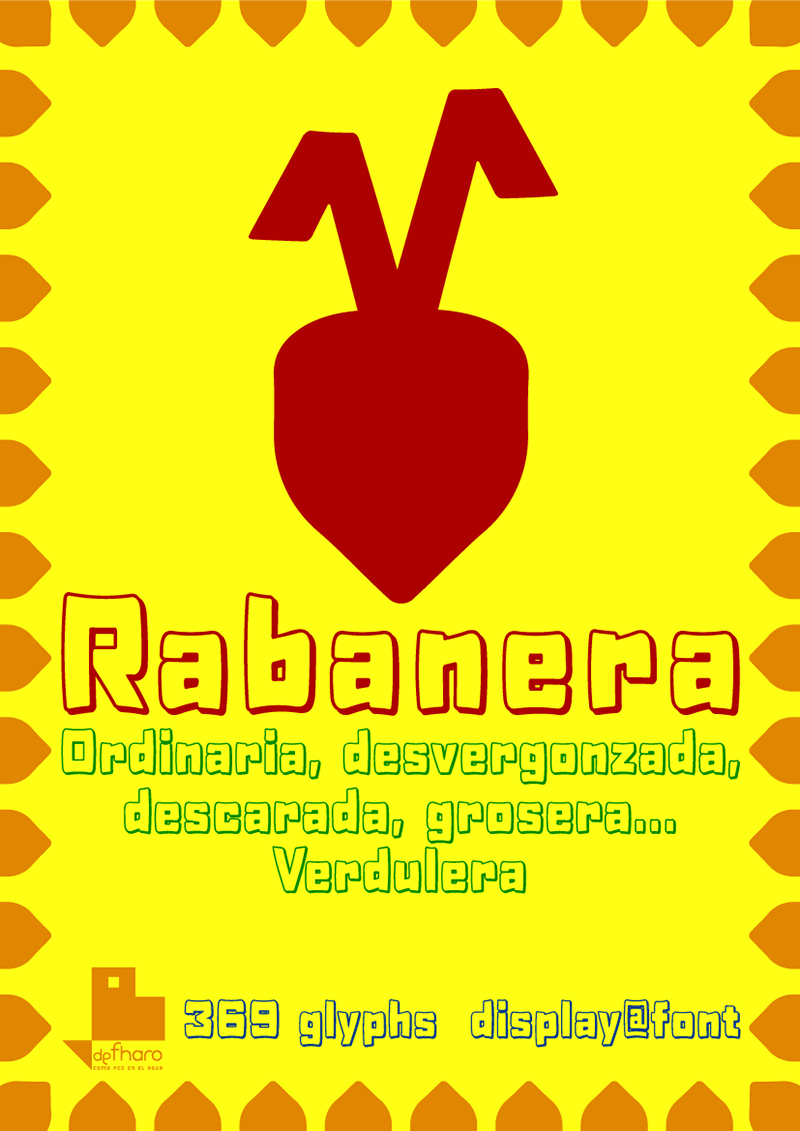
Rabanera es una nueva fuente tipográfica, basada en mi anterior diseño Hobby of night, de estilo outline + shadow, de caracter divertido esta fuente la puedes usar en diseño gráfico o editorial, por su morfología se la puede denominar: Display font.
Ideal para cualquier diseñador gráfico, esta fuente le servirá para encabezados o grandes titulares y rótulos, de perfecta legibilidad y lectura en frases largas.La tipografía está compuesta de 369 glifos, son los necesarios para usar la fuente con todos los idiomas europeos basados en el Latín, incluye el símbolo del euro y el icono del rábano construido con la letra D mayúscula, el símbolo duplicado de Radical y el símbolo less para la punta.
El nombre que he elegido para esta fuente es un ejercicio de Naming-marketing divertido que completa el proyecto, la acompaño con una lista de sinónimos, elegidos para crear espectación, a partir de la primera definición de la RAE.Según esta definición de la RAE [Rabanera]: 1. adj. coloq. Dicho de los ademanes y del modo de hablar: Ordinarios o desvergonzados.
Verdulera, ordinaria, descarada...
Estilo: Display
Proporción: Regular